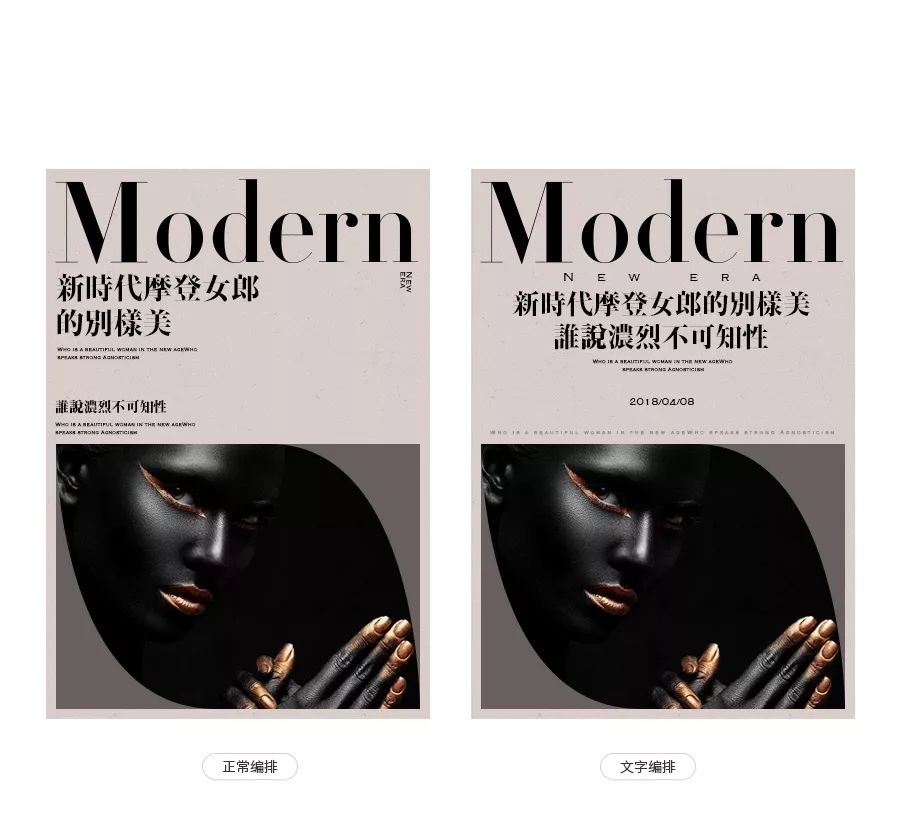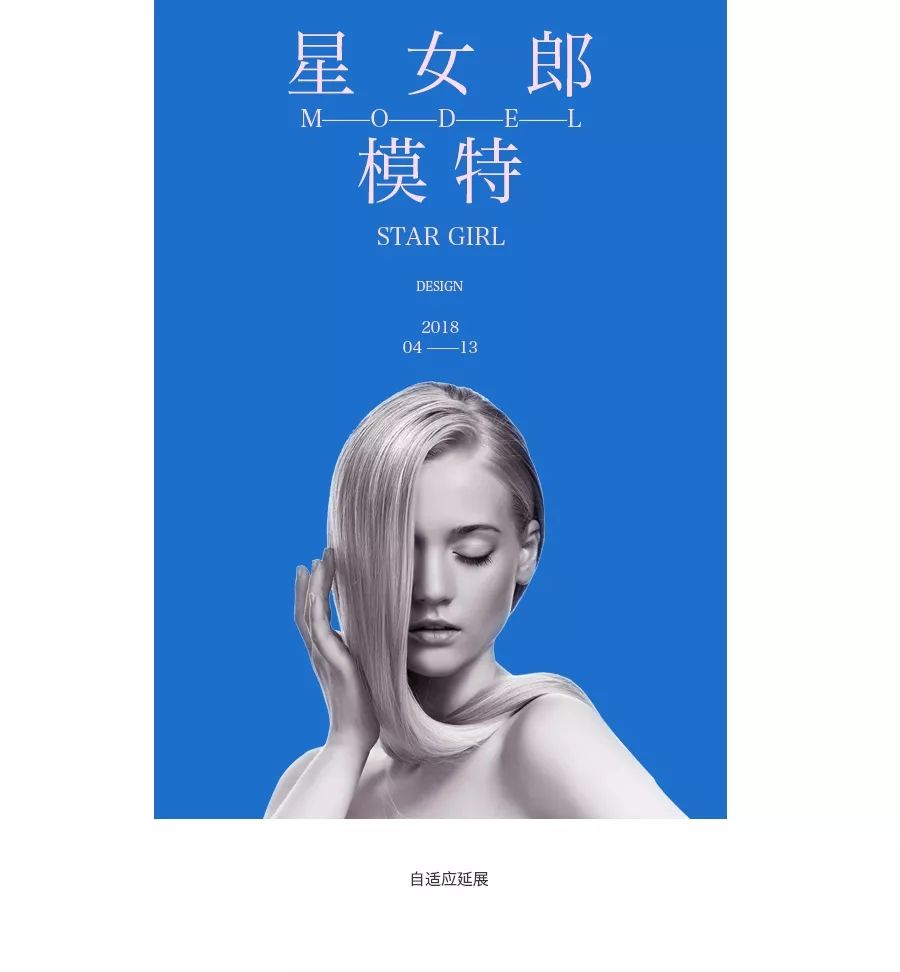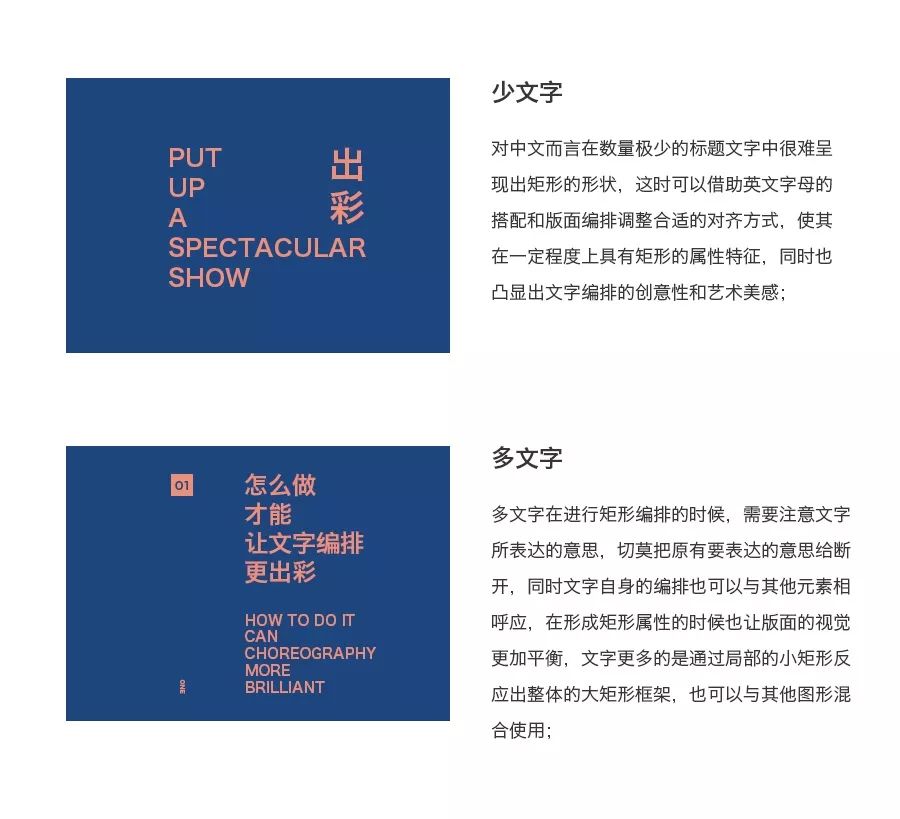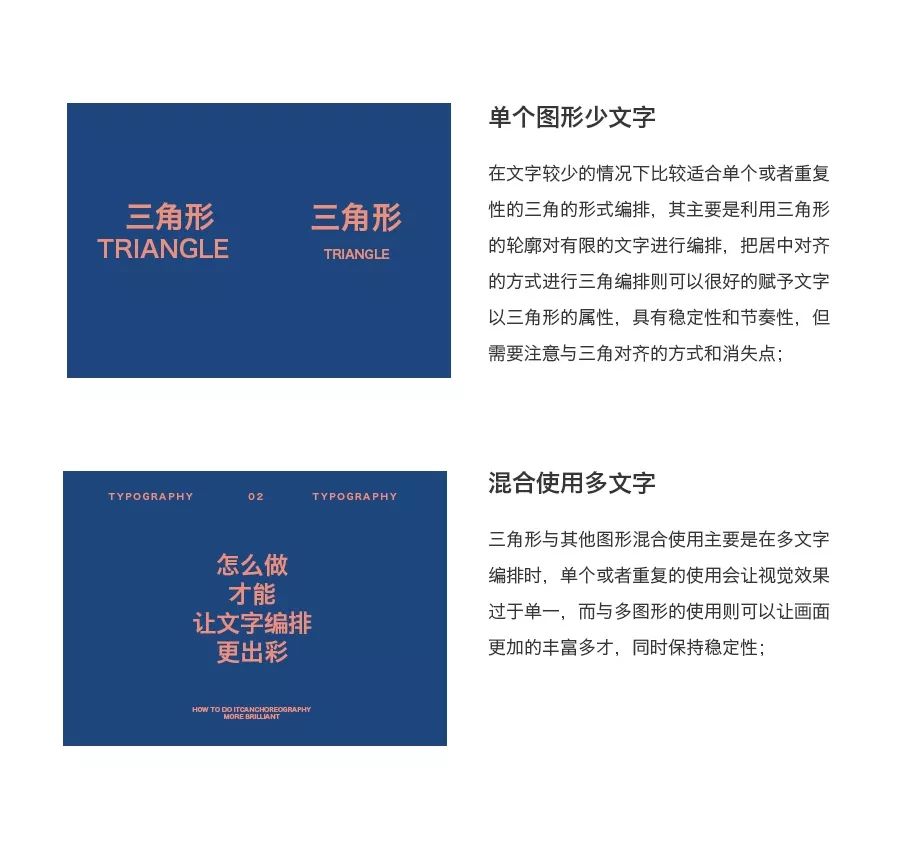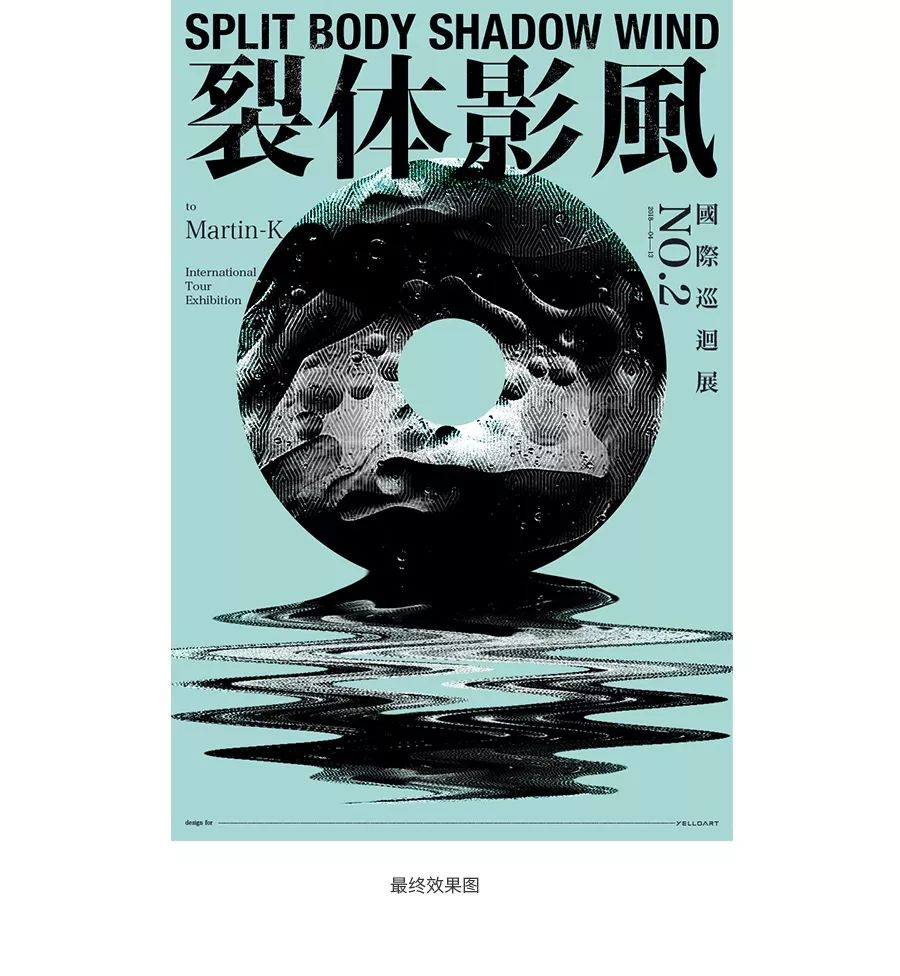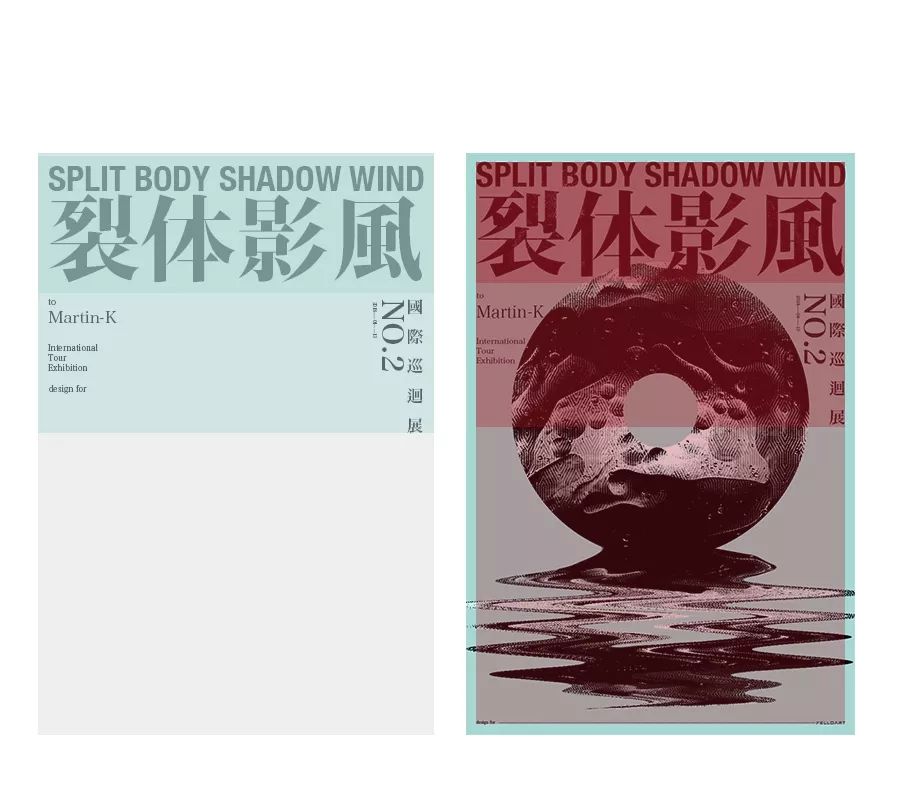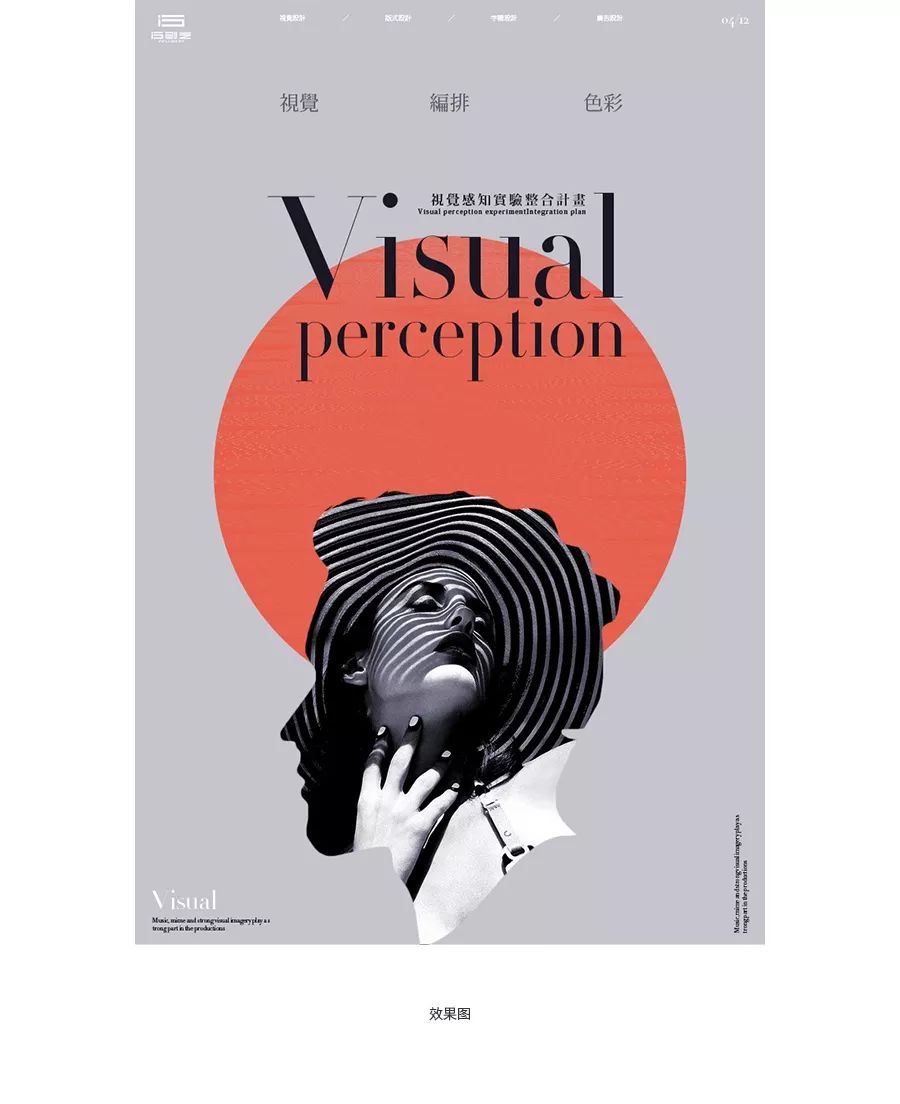
怎么做?才能让文字编排更出彩
在之前视觉设计文章中,我把视觉设计大致罗列了四个方向,更多的是希望能够为大家带来一些努力方向,在设计的路上不那么困惑迷茫,视觉设计本身涵盖的范围就比较广,同时也没有什么衡量的标准和具体的特征,只有依赖于商业的服务中才能更加客观的体现出最终的视觉价值;很多小伙伴留言说太笼统了(也有不少水军偷偷潜入),在罗列的四个方向中字体的应用在《字言字语》系列文章中已经写的比较多了,大家可以自行翻阅学习,本篇文章同样立足于视觉设计的角度,对字体的编排进行详细的赘述,在视觉设计中通过什么样的方式才能让文字编排更加出彩;
文字编排是一种艺术创作过程,是通过艺术地手段将平面中的文字组成要素,在符合阅读逻辑的前提下加以重新组合调度,并在结构及色彩上作整合安排的一种视觉传达方式,它是一种重要的视觉传达语言,是一门相对独立的平面设计艺术,也是设计师必须要熟练掌握的一项基本技能。
图1:
很多情况下,当我们把文字进行有序的排列之后就会误认为是编排,其实只是把文字正常的输出来而已,并没有进行任何的修饰和编排,虽然是大家都比较熟悉且容易认知的类型,但作为设计师则会失去应用的职责,在不添加任何效果修饰的情况下,正常的文字编排很难出彩营造较好的视觉效果
图2:
而当我们针对固有的文字信息通过艺术的手段对其进行重新组合,在保证信息有效传递的
同时也使文字自身具有一定的视觉艺术效果,这种处理方式只是针对文字本身的结构特征
重组,并非是依赖于整个版面使其具有较好的视觉效果,这种方式我们则可以称为文字编
排设计
文字也是版式中的重要元素之一,在利用整个版式对文字进行合理的排布时而不是针对文字自身进行编排时,则可以称之为版式设计,而在设计中两者通常结合在一起进行使用,让画面的视觉效果更加出彩;
图1:
实际应用当中,文字在经过层级和大小对比的基本划分处理之后,按照正常的阅读习惯使文字井然有序的进行排列,这种方式也是常规的编排形式,虽然没有什么大的问题,但就视觉而言,画面和文字都还不够出彩,难以满足设计的基本艺术表现;对设计师而言,不仅仅只是把文字进行有序的排列;
图2:
当对所有的文字划分好层级和调整好对比之后,并对文字之间的关系和排列融入一定的艺术美感表现,在保证信息可以有效准确传递的同时,使文字更加的出彩耐看,同时也直接影响到整个画面视觉表现,文字自身的编排可以说是最基本的技能之一,好的文字编排可以为视觉效果起到积极的作用;
版文编排则是在文字自身编排的同时又对版式进行适当的划分,顶部大标题中则是利用了英文的字体结构进行编排,使小英文字母与左边的中文相呼应以保证版面和文字编排的平衡,在设计中通常会使用到两则结合的情况下进行使用,同时也体现出了文字的自适应和它适应;
在对文字编排设计时需要对文字的机构基础有一定的了解,很多情况下文字的编排即是对结构的编排重组,在调整字与字之间的结构时完成较为出彩的,具有艺术表现的文字编排;文字的结构可以根据中文和英文两种不同的字体语言进行划分;
中文是基于方格的基础上创作而成,单个文字的结构只存在于方格内,而文字编排则是利用单个文字和文字与文字之间的结构调整,打散重组等等艺术的设计手段完成具有一定艺术性美感的文字编排;
中文字体结构在基于方格的基础之上进行纵向或者横向延伸,不管如何延伸均是基于田字格把方格划分曾四等份,给予文字编排更多的可依据空间,抛开创意文字和特殊文字结构来说,即使不会字体设计,同样可以利用相对稳定的字库文字结构做一些精致的编排;
在相同的一句文字当中,把整句话的首字提取作为主视觉,并把文字之间原有的结构适当的打散重组,大文字和小文字同时占据一个方格,使其以新的结构形式呈现,增强文字编排的视觉效果;
中文字體的結構相對來說比較統一,但缺少節奏感,在文字編排時則需要對文字的結構適當的調整,以增加文字的節奏感營造舒適具有創造性的文字編排,同時滿足文字編排自身
的自適應提升視覺效果;
在英文字体中,无衬线体和衬线体的结构区别不是太大,其主要差别在于大写與小写的字母上,而单个字母的结构应用更多的是在于内部负空间和自身的结构上,英文字体相对中文来说,利用结构进行编排起来更加的灵活多变,但也是基于小写字母上拉伸和下拉伸之间的空间内加以利用;
单个字母
在英文字体中,针对单个字母进行编排时皆是以自身结构为出发点,对其结构和内部负空间加以利用,使其达到具有艺术性编排的目的,相较于大写字母而言,小写字母则会比大写字母多了一个拉伸的可操控部分;
词句
当英文以词组或者句子出现的时候,通常会伴随着大小写英文使用法则混用的情况,这样就会使得英文的节奏感更加强烈和多变,同时也为编排留下很多可操作的空间,无衬线体词组内部结构可操作性相对衬线体而言空间较小,需要注意文字的选择;
文字的自适应和它适应是相辅相成的,是由小见大,由局部到整体的过程自适应如果是细节,它适应则是骨架方向;文字即是独立的个体存在,也是应用的自身功能价值体现,在设计中无处不在的文字,其表现方式多种多样,除了文字自身适应和字与字适应以外,还需要考虑其在不同场景和不同表现形式中的它适应,以满足视觉画面的需求;
图1:
对文字而言,大多数处理的方式只是把精力花费在文字的选择,调整文字之间的间距和行
间距上面或者调整一下对比等一些简单的常规处理,从而忽略了对文字艺术性的编排设计,最终则是平淡的排列,并没有让文字自身具有一定的视觉效果;
图2:
在现有的文字基础之上,先考虑所有文字进行自身的编排,使其本身具有一定的视觉效果,即使在没有画面的置入的情况下也同样会出彩,而文字自身的编排就是文字之间的自适应能力,在这种情况下会把文字的选择,间距,行距等等一系列细节问题暴露出来,这是一个由局部到整体严谨把控;
当把文字自身的自适应处理好之后,不管如何应用只会让画面更加的出彩,但同时还需要文字编排的它适应;
图1:
在实际案例中更多的是以正常的保守方式进行排列,或者是因为画面的主体太过于特殊和
呆板,导致了我们对画面的想象局限性,即使做在文字之间做了一些对比和细小的变化,
但却难以撑起整个画面的视觉效果,而让想要表达的主题内容大打折扣;
图2:
当根据画面的构图或者版式对文字进行编排时,更多的会依赖于版式的排布只重视文字在
画面中的位置,大小,而文字与文字之间的自适应则会忽略,虽然没有太大的问题,但却很难让整个画面更加出彩一些,以满足我们理想中最终视觉效果;
自适应与它适应则是互为依存的,如果画面中只重视自适应在实际应用中则会显得不太协调,即使文字编排比较出彩,但对整体来说则却少把控,而只重视它适应则会让画面的出
彩空间受到局限;
在设计中文字编排可以说是最基础的基本功,同时也是最难的基本功,是伴随着设计职业生涯不可或缺的必备技能之一,不管在任何设计行业中设计师经常都会与文字打交道,即使单一的文字编排也可以从其中看出设计的功力是否深厚;对于文字编排来说,在抛开版式的束缚之后,同样可以利用几何图形的方式使文字编排达到我们理想中的效果,以提升画面的视觉;
在设计中文字编排矩形化是使用最为普遍的方式,但也是集文字的自适应和它适应以及文字结构为一身的综合使用,是通过局部反应整体的直接表现,其在画面中主要可以对视觉产生平衡的作用,不管是横向和纵向的左对齐还是右对齐都可以以矩形作为衡量的工具,同时也与中文造字的基础不谋而合;
以文字需求为例,这种情况通常是一些偏向概念的表达,对于概念的表达使用几个图形最为合适不过了,对文字信息分析之后我们要根据文字确定画面中的主体;
新建一个画布,然后针对需求文字信息分析之后,以圆形作为画面的主体,接着对主体进行适当的刻画处理,以满足文字所要表达的具体的内容,使其以可视化的方式呈现给观者;
图1:
根据文字要信息要表达的意思对设定的主体图形进行处理,找到一些相应的素材直接剪贴蒙板到圆里面,并调整好合适的展示位置,然后对圆形添加内阴影的图层样式,调整相应的参数,以达到具有质感立体的效果,在简单的处理好单个图形之后,与文字信息的“影”字
还不太符合,需要进一步对主体进行修饰处理;
图2:
把与圆形相关的所有图层全部转换为智能对象,然后并复制一层,执行滤镜中的扭曲-波浪化,这样做主要是想表现出影和裂体的感觉,然后调整波浪化的图层与圆形结合,使其成为圆形的倒影,波浪化的处理和最终的结合需要在不断的调试中慢慢确认下来,以更好的贴切需求想要表达的主旨意思,对图形处理完之后接下来就是对文字信息的处理;
图1:
在处理好画面的主体之后,把所有的中文信息再翻译成英文同时对所有的文字信息根据版
面进行集中性的编排,并对文字的选择,间距,大小等等做相应的调整,以矩形的编排形
态形态呈现,这时则时以信息准确传达为基础,反应文字编排的自适应;
图2:
把文字编排好之后置入到画面,而这时主要时考虑文字编排的它适应是否可以与画面融化一体,在保证信息可以准确传达的情况下具有一定的视觉效果为了让文字编排的它适应和画面的平衡更加和谐统一,把不重要的英文调整到最底部,使其与整体形成一个统一的整体;
在设计中很多人认为居中的对齐方式最不好把控,不知道该如何对文字段落,大小进行合适的编排才能让视觉效果更加舒适,尤其时在矩形的画面中很难找到相应的对齐参考依据,而三角形则可以很好的解决这一问题,让文字居中对齐的方式有一个很好的艺术表达;
新建一个画布,然后把主体置入到画面当中,其主题是要表达一个视觉整合的意思,在进行分析之后我们需要改变主体的形式以满足需求;
图1:
根据对主题的分析,以现有男性的主体作为轮廓,然后添加一个女性,使其代表整合的主
题,然后在主题后面添加一个圆,并对圆添加一个纹理,使其具有质感,圆在画面中居中
对齐,调整主题的位置以便为后续的文字留下编排的空间;
图2:
以分栏法把整个版面划分成四等份,主体部分和文字信息重点则是以对称形式占据视觉中
心,值得注意的就是文字重点则是以矩形的编排形式作为轮廓载体,而其他文字则是以对
称三角轮廓载体,在局部松散的情况下以外轮廓三角平衡画面视觉;
圆形在文字编排中相对应用的较少一些,由于自身的特点通常会在一些特殊的表达中应用,不易大面积的使用或者作为文字编排的参考,相对难度较大不以掌控,对于正常的阅读来说容易给人们造成灵活,阅读不便的感觉,在版面中恰当的加以使用圆形时则可以很好的体现出创意性;
新建一个画布,把主体置入到画面当中,以带毛边的圆形作为主体,同时也是大家经常会遇到的圆形主体,然后打破常规形式编排以让画面更加出彩;
图1:
先针对基础圆形主体适当的进行处理,对其添加相应的质感以增强其视觉的表现力,处理
方式则是寻找相应的纹理素材直接剪切蒙板到圆形当中,并适当的调整位置以及所要表现
出的质感,根据想要的效果执行相应的处理方式即可;
图2:
在处理完主体之后,对于文字的编排来说,以正常的矩形或三角形式正常编排则会显得
太过于形式的平淡,而利用圆形的编排则可以很好的于主体相呼应,但针对整体而言,版
面则会显得过于灵活,在这种情况下则需要对文字编排的它适应加以调整;